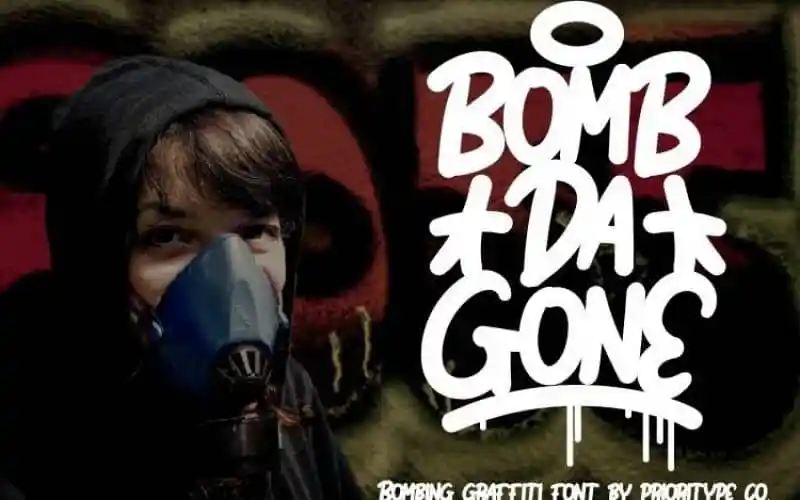
A Bomb Da Gone Display Font é uma excelente escolha para designers que buscam criar designs modernos e vibrantes. Esse fonte de exibição foi criado com um estilo engraçado e levemente fantasioso, inspirado na pintura artesanal. Ela faz da letra uma ferramenta poderosa, especialmente quando se trata de transmitir design urbano gráfico. Adaptable a diversos tipos de mídia, essa fonte torna sua presença notável em produtos como camisetas, skateboards e capas de álbuns. Tanto os itens que você pode encontrar nas lojas quanto as criações únicas que você pode fazer para uma coleção autêntica ou personalizada. Também é perfeita para landing pages, postagens no Facebook ou Instagram, outdoors, adesivos e até mesmo eventos. Através das pré-vizualizações acima, você terá uma ideia clara de como essa fonte pode moldar seu design. A Bomb Da Gone Display Font não apenas oferece um diferencial visual atraente para seus projetos, mas também permite que você apresente sua marca de maneira fresca e relevante.